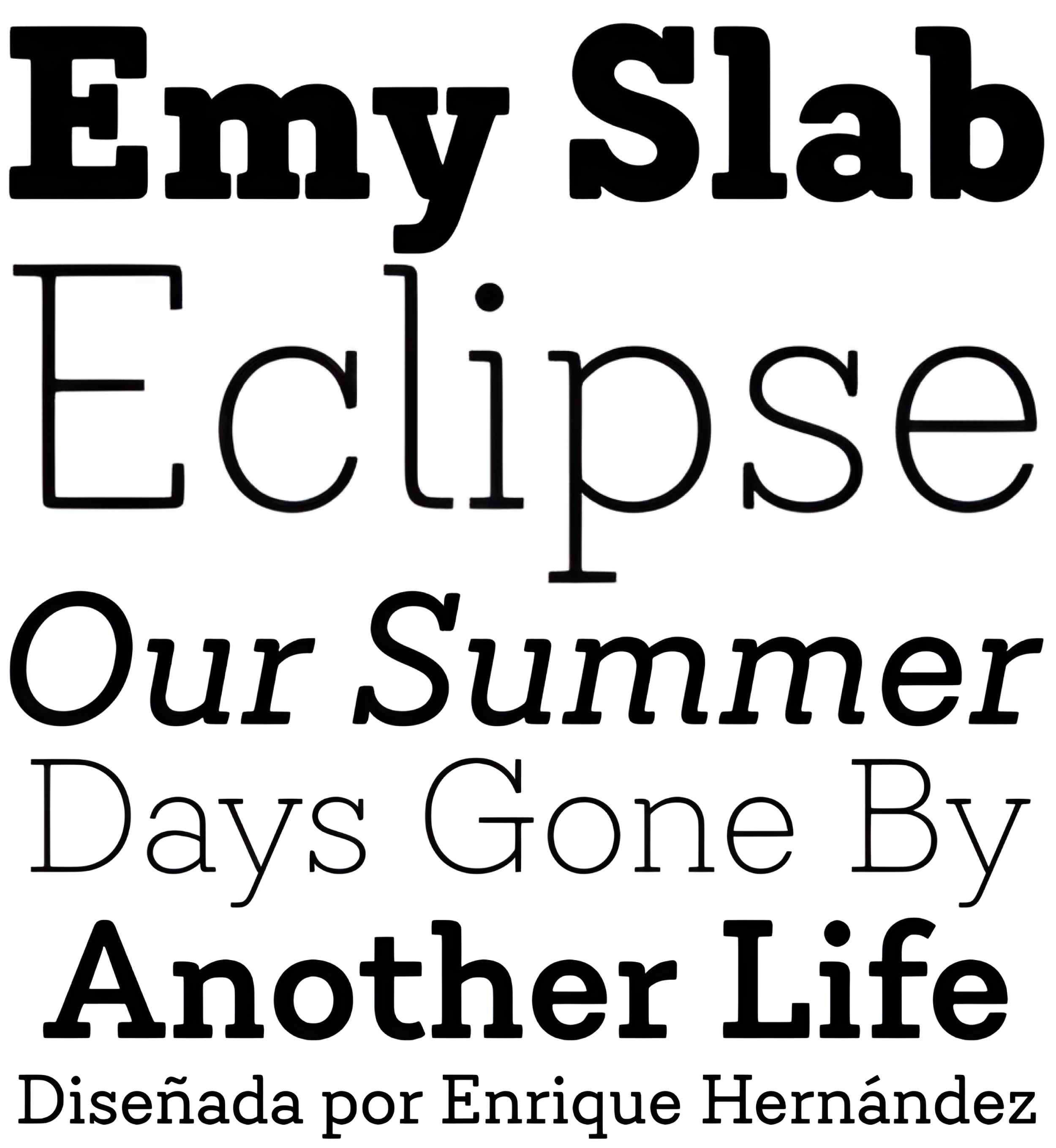
| Créditos | Enrique Hernández |
| Descripción | Emy Slab es una fuente con gracias basada en las proporciones clásicas de los tipos egipcios, pero con terminales suaves que le dan un aspecto más amable y moderno. Emy Slab consta de dos subfamilias de 7 pesos, que van de Thin a Black, con cursivas a juego, lo que da como resultado un total de 28 fuentes. La versión estándar es ideal para diseño editorial, azulejos, libros, revistas, diseño corporativo y todo tipo de publicaciones. La versión Alt -por sus características de visualización, formas asimétricas y aspecto contemporáneo- es muy adecuada para logotipos, marcas, envases y uso en web y Tv. Emy Slab contiene un conjunto de 440 caracteres compatibles con 208 idiomas diferentes. |
| Familia(s) | Thin, Thin It, Ultra Light It, Light, Light It, Regular, Regular It, Semi Bold, Semi Bold It, Bold, Bold It, Black, Black It, Alt Thin, Alt Thin It, Alt Ultra Light It, Alt Light It, Alt Regular, Alt Regular It, Alt Semi Bold, Alt Semi Bold It, Alt Bold, Alt Bold It, Alt Black, Alt Black It |
| Estilos | 28 |